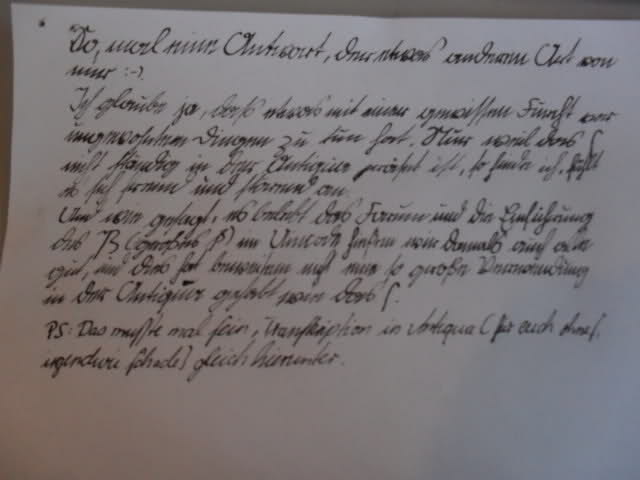
Haa! ... noch einer der ?o schreibt. Mir gefällts, es belebt das Forum. :cheer:
Hmm ... bei einer Fraktur – ja! Aber doch nicht bei einer Antiqua – ich finde, das lässt sich furchtbar lesen! :neenee:
Haa! ... noch einer der ?o schreibt. Mir gefällts, es belebt das Forum. :cheer:
Hmm ... bei einer Fraktur – ja! Aber doch nicht bei einer Antiqua – ich finde, das lässt sich furchtbar lesen! :neenee:
Das ist Gewohnheitssache. Grundsätzlich läßt sich auch Antiqua mit beiden s-Formen besser lesen, da man die Wortfugen schneller erfaßt.
Stimmt schon ... ich bin dafür bestimmt einfach nur zu jung. (Bei mir flackert da überall nur so was f-ähnliches in den Wörtern herum. Geht bestimmt allen jungen Leuten so?!)
Ich würde mich nicht als alt bezeichnen und habe mein Faible für gebrochene Schriften mit 15 entdeckt, lesen konnte ich sie aber schon vorher und das fällt doch unter „junge Leute“, oder?
Stimmt schon ... ich bin dafür bestimmt einfach nur zu jung. (Bei mir flackert da überall nur so was f-ähnliches in den Wörtern herum. Geht bestimmt allen jungen Leuten so?!)
nun, ich lese quasi täglich die verschiedensten sprachen und schriften, doch ist das lang-s schlicht ungewohnt in antiqua gesetzten texten. es ist zwar nicht unerkennbar, aber weil es so unerwartet ist, ein lesestopper.
Ich bin ehrlich ge?agt ein kleines bi??chen verwundert, da?s das lange s (?) auch hier in einem Typographieforum auf – na ?age ich mal – nicht uneinge?chränkte Zu?timmung ;) bzw. um das Kinde beim Namen zu nennen Vorbehalte ?tößt. Das zeigt mir, wie ?tark der Gebrauch des langen ? nicht nur aus der Mode gekommen, ?ondern teilwei?e ?ogar überhaupt nicht mehr ver?tanden wird :( – um?o wichtiger ?cheint es mir zu ?ein, die?e Tradition auch weiterhin zu pflegen, ?o da?s ?ie eines Tages nicht vollkommen ver?chwunden ?ein wird. Und da ich auch noch unter 30 bin (¿mu?s ich mich jetzt eigentlich alt fühlen?), werde ich das hoffentlich auch noch ein paar Tage lang machen können.
Mit Steffis Forumlierung der exaltierten, aber liebenswerten Marotte kann ich übrigens recht gut leben – ich ?chreibe das ? keinesfalls, nur um anderen das Leben zu er?chweren – es i?t halt einfach eine per?önliche typographi?che Note. Herzliche Grüße an alle Antiqua-Nutzer, Frakturfreund
Warum?
Die Frage ist doch eigentlich, ob das lange s überhaupt im Kontext des Antiqua-Satzes im Gebrauch gewesen ist. Wenn ich meine schnelle und unsaubere Recherche richtig deute, dann ist es im Grunde z.B. in Deutschland nur von sehr untergeordneter Bedeutung gewesen. In England und Frankreich ist das langes s im Ende des 17. Jahrhunderts ziemlich rapide verschwunden; da wurden in Deutschland aber vorwiegend gebrochene Schriften verwendet. Die Verwendung in den vergleichsweise raren Antiqua-Texten war hingegen nie einheitlich und hat sich sehr schnell zum Satz ohne das lange s entwickelt. Wenn das so stimmt (und ich bitte da ausdrücklich um Ergänzung/Verbesserung falls das nicht der Fall sein sollte), dann wird durch den Gebrauch des langen s im Antiqua-Satz nicht wirklich ein »Kulturgut« bewahrt, sondern etwas eingeführt, was eigentlich nie besonders üblich war.
Das Lange s in der Antiqua kommt auch in frühen Antiqua-Drucken aus Italien (Aldus & Co) vor. Insofern "gibt" es das lange s schon auch in der Antiqua – die Muster sind aber 500 Jahre alt.
Da habe ich mich etwas mißverständlich ausgedrückt; daß es das lange s in der Antiqua gegeben hat bestreite ich nicht. Nachweise gibt es dafür viele. Ich meinte viel eher: ist das lange s im Deutschen jemals konsistent im Antiqua-Satz verwendet worden?
Also, ich finde Schrift und ihre Geschichte ungeheuer spannend und mag auch Traditionen gerne – aber mit dem Lang-? in modernen Antiquatexten tue ich mich immens schwer. Ich habe ein Buch (Wirklich gute Logos erklärt, Stiebner-Verlag), in dem das Lang-? komplett durch alle Texte durchgezogen wird und ich stolpere über jede einzelne Anwendung. Ich lese immer ein „f“ und das wirkt dann wie ein Sprachfehler …
Der Mensch – ein Lesegewohnheitstier. :?
Grüße, Kathrin
… Das zeigt mir, wie ?tark der Gebrauch des langen ? nicht nur aus der Mode gekommen, ?ondern teilwei?e ?ogar überhaupt nicht mehr ver?tanden wird :( …
Das Lang-s war keineswegs Mode, sondern Bestandteil der Schrift. Das Verständnisproblem liegt nicht bei uns Nicht-Anwendern, sondern bei dir.
… – um?o wichtiger ?cheint es mir zu ?ein, die?e Tradition auch weiterhin zu pflegen, ?o da?s ?ie eines Tages nicht vollkommen ver?chwunden ?ein wird. …
Dann bitte dort wo es eingesetzt wurde. Du trägst ja auch keine Holzklapperl zum Businessanzug, nur weil die Tradition eventuell verloren gehen könnte.
… Und da ich auch noch unter 30 bin (¿mu?s ich mich jetzt eigentlich alt fühlen?), werde ich das hoffentlich auch noch ein paar Tage lang machen können. …
Und wir müssen das ausbaden?
… Mit Steffis Forumlierung der exaltierten, aber liebenswerten Marotte kann ich übrigens recht gut leben – ich ?chreibe das ? keinesfalls, nur um anderen das Leben zu er?chweren – es i?t halt einfach eine per?önliche typographi?che Note. Herzliche Grüße an alle Antiqua-Nutzer, Frakturfreund
Du erschwerst das Leben aber leider. Das ift fo. 8)
das versal-ß ist ein buchstabe der fehlte und gebraucht wurde.
nee, gebraucht wurde der nicht. hast du ein versal-ß in letzter zeit irgendwo gesehen? und ich meine nicht diplomarbeiten zu dem thema oder bibliophile publikationen, die lange nach einem wort mit ›ß‹ im titel gesucht haben, um zeigen zu können, wie kultiviert sie sind … man hat so viel seltener gelegenheit, ein versal-ß einzusetzen gegenüber einem lang-s, weswegen es deutlich weniger nervpotenzial hat als lifpelnde traditionaliften.